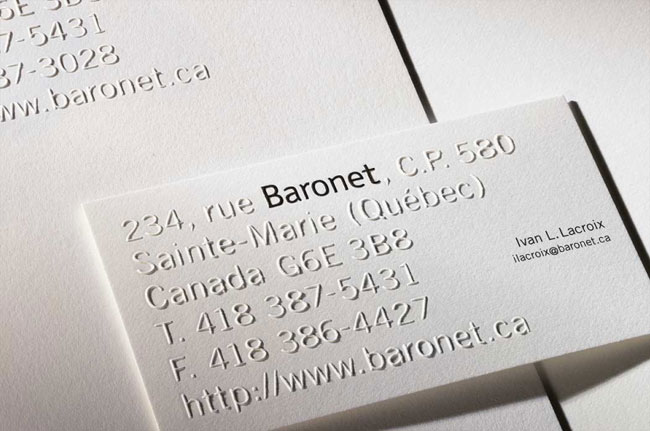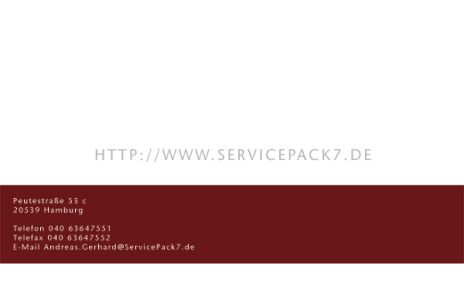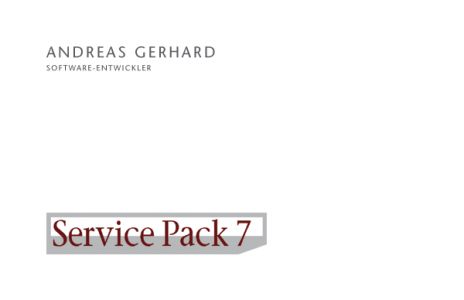
Mal ein paar ganz dumme Fragen: Wie bist Du denn jetzt zu dieser Gestaltung gekommen? Warum das Format? Warum die Auswahl an diesen Kontaktdaten? Warum diese Schrift? Warum die Versalien, warum die eine Zeile auf dem Kopf und Autorin kursiv? Warum schwarz auf weiß (ich wiederhole mich ;))? Warum Fernruf, warum E-Mail?
Das sind ja Fragen über Fragen :o Also gut: Das Ganze ist mal eine fiktive Karte für eine fiktive Autorin. Format/Datenauswahl entsprechen glaub ich der Norm, oder? Autoren schreiben i.a.R. Bücher, daher die Garamond -- sie ist eine typische Buchschrift. Die Versalien sind Kapitälchen, die lediglich ein wenig an Stärke bekamen. Sie sollen, ebenso wie die kursive Berufsbezeichnung, die Informationen nur sortieren. Die Kopfzeile füllt den rechten Leerraum und ist das "andere" :) Schwarz/Weiß ist bei mir mal zunächst jeder Versuch -- Farbproben kommen erst wenn alles andere passt, wg. dem schönen Papier, und Telefon/E-Mail sind eigentlich normale Kontaktdaten. Gut, den "Fernruf" kann man freilich auch "Telefon" nennen, aber die E-Mail ...?
Soll einfach mal jeder, der Lust dazu hat, seinen Senf dazu geben, auf dass man mal mitbekommt, was beim Gestalten so überlegt wird. Insofern nur erst einmal ein erster Vorschlag. Mal schauen was dabei herauskommt und ob das Resultat dann schließlich auch wieder völlig "normal" ist.
»Normal« ist Scheckkartenformat. 85 × 54 mm meine ich. Insofern scheint Dein Format wesentlich schmaler – was ich gut finde. Du willst »mal etwas anderes« argumentierst aber mit »typische Buchschrift« und »entsprechen der Norm«. Das Andere ist bei Dir lediglich die Kopfzeile, die den rechten Raum füllt – bißchen wenig oder ;)
Verstehe mich nicht falsch. Ich will Dich einfach zum Nachdenken anregen, wissend wie schwer es ist Konventionen zu brechen und etwas außergewöhnliches zu machen. Du hast jedoch so viele Möglichkeiten an denen Du schrauben kannst (und meiner Meinung nach gehören Farbe und Papier nicht zuletzt dazu – um wieder darauf rumzureiten) und beschränkst Dich darauf, eine Zeile verkehrt herum zu setzen :?
Ich muss jetzt einfach mal den Herrn Bleisetzer etwas unterstützen. Ich streiche meinen Senf also auf besagtes Kärtchen Tobbers (das Schriftmuster-Zettelchen).
Etwas verallgemeinert sicher, das Folgende, trotzdem: So setzte mancher Architekt (Architektinnen eher ausgenommen) seine Firmendaten, wenn er's halt in grenzenloser Selbstüberschätzung selber setzen wollte. Versal, alles auf dieselbe Satzbreite - Mauern halt ;-) Das kann spannend sein, muss aber nicht. Sonderlich originell ist es wie gezeigt ganz gewiss nicht.
Eine Frage vorweg: Hast du tatsächlich einen "echten" Kunden für die ganz-frei-in-der-Gestaltung-Visitenkarte? Dann solltest du bei dieser Person beginnen: Name, Beruf, persönliche Vorlieben - oder dein voreingenommener Eindruck ... Ich glaube, dass man mit einer "Mustermann"-Lösung immer nur in einer Standard-Gestaltung enden wird. Ich brauche zumindest immer einen ersten konkreten Ausgangspunkt für eine kreative Lösung - selbst wenn ich ganz woanders ende, muss ich die Reise doch irgendwo beginnen.
WAU: sehr cooool! Wie geht denn sowas? Ist das gestanzt oder gedruckt? (Sehr schöne Arbeiten auf der Seite!)
Norbert P.: naja, sagen wir mal "Quasi-Kunden" :) also eher "Geschäftsfreunde". Wir kommen alle aus der schreibenden Zunft, ich setzte zudem noch Bücher (da ist der Gestaltungsspielraum eher gering und die Kunst jahrhundertealt -- insofern hat TYPOGRAFSKI nicht gänzlich unrecht). Wir fahren nun nächste Woche auf die Buchmesse (Pflichttermin f. Autoren) und die Herrschaften wollen "etwas andere" Visitenkarten und baten mich mir mal Gedanken zu machen. Das ist also nix für Kohle -- eher ein geschuldeter Gefallen.
Sowohl als auch, sieht man doch.
sowohl als auch?
es ist geprägt und gedruckt, wobei der druck selbst totaler quatsch ist,
sieht aus wie nachträglich eingedruckt.
Ich bleibe dabei: die Karte genügt sicherlich ihrem Zweck. Nebenbei: ich habe beruflich recht viel mit Leuten aus der IT-Brache zutun. Verglichen mit vielem, was ich da bereits zu sehen bekam ist das allererste Sahne.